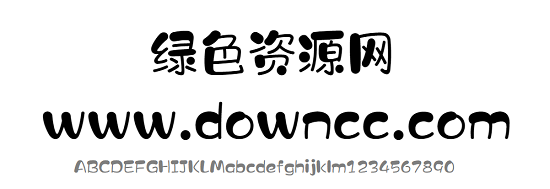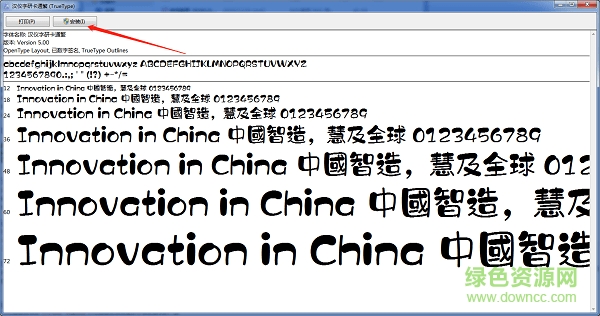
漢儀字研卡通體是由漢儀字體全新發(fā)布的卡通版字體,此款字體整體上整體看起來非常的圓潤,每一個字都能夠為用戶呈現(xiàn)一種非??蓯鄣漠嬶L,使用于各個版面的設計等等,需要的用戶就來綠色資源網下載吧!
漢儀字研卡通一款有著動漫卡通藝術字氣息的字體,筆畫圓潤可愛,萌萌的畫風,整體結構簡單有趣,帶給你一種萌萌的既視感,適用于海報設計,游戲動漫設計的設計等,非常不錯的一款字體!